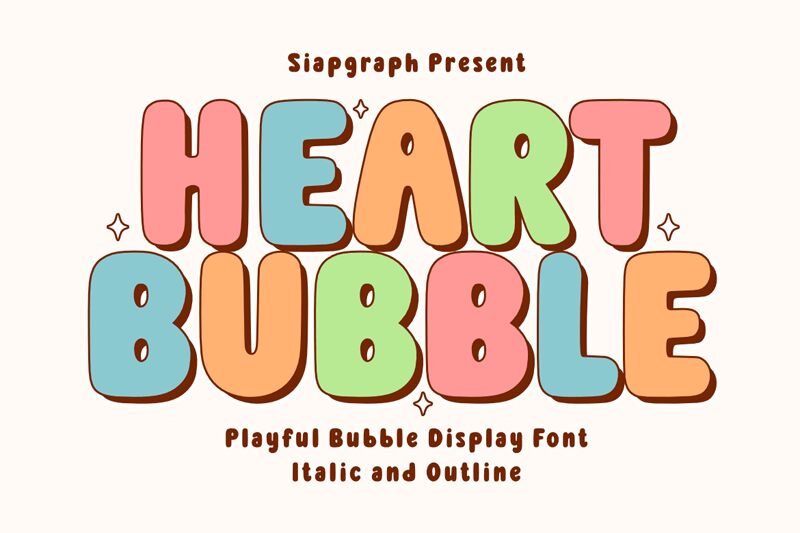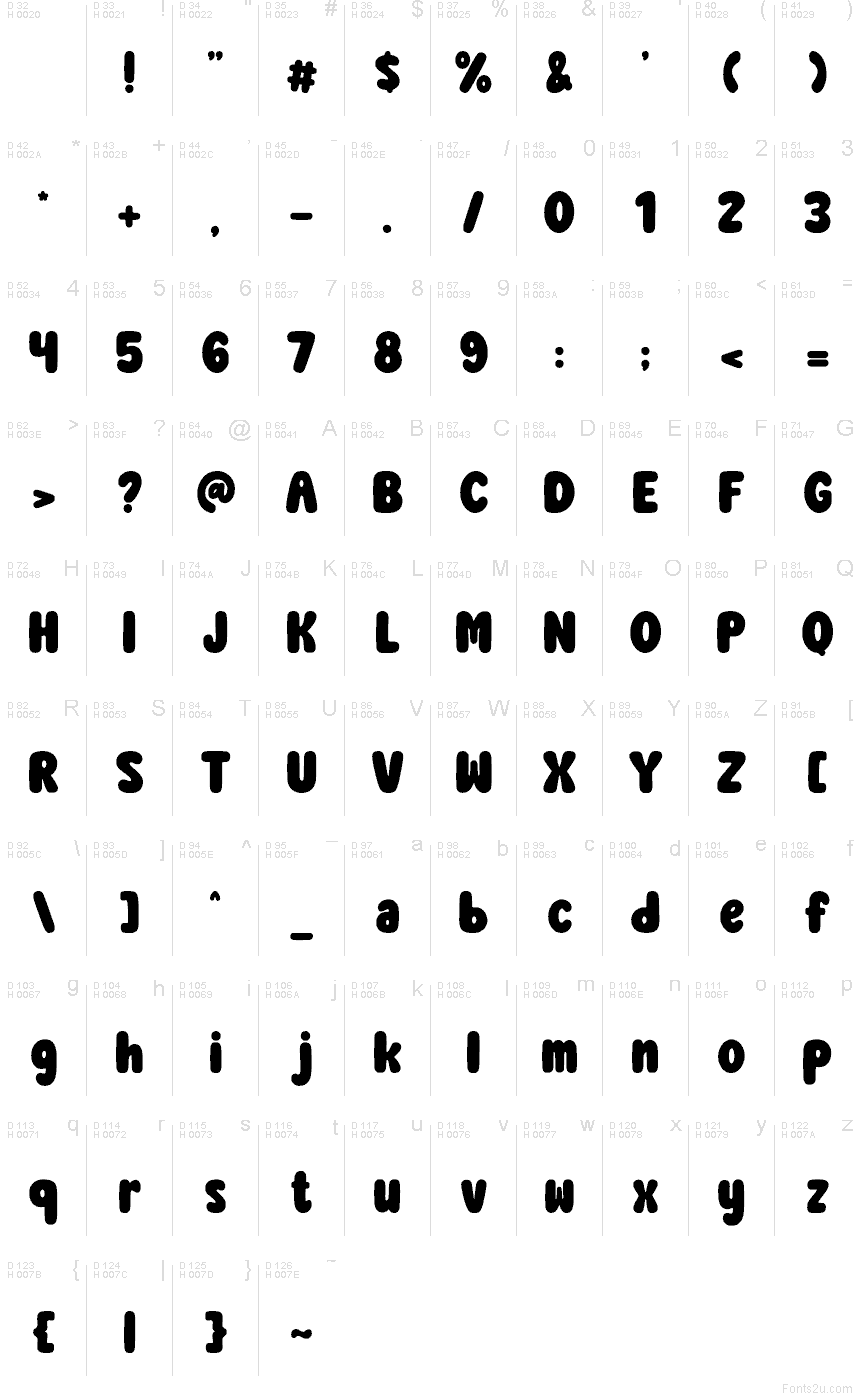
Heart Bubble od SiapGraph to darmowy, rysunkowy font typu display. Jego miękkie, pękate litery sprawiają wrażenie, jakby były nadmuchane, a nie tylko zaokrąglone. Formy są masywne i przyjazne, z głębokimi łukami, krótkimi łączeniami i odręcznym charakterem, który nadaje tekstowi uroczy, „miękki” rytm.
To naturalny wybór do opakowań dla dzieci, identyfikacji wizualnej słodyczy, zaproszeń na przyjęcia, projektów naklejek oraz radosnych postów w mediach społecznościowych, gdzie liternictwo powinno być ciepłe i optymistyczne. Jako darmowy font, świetnie sprawdzi się również w krótkich nagłówkach, tytułach i logotypach, które korzystają z tych pluszowych, bąbelkowych kształtów, nie wpadając przy tym w zbyt wygładzony lub retro styl.